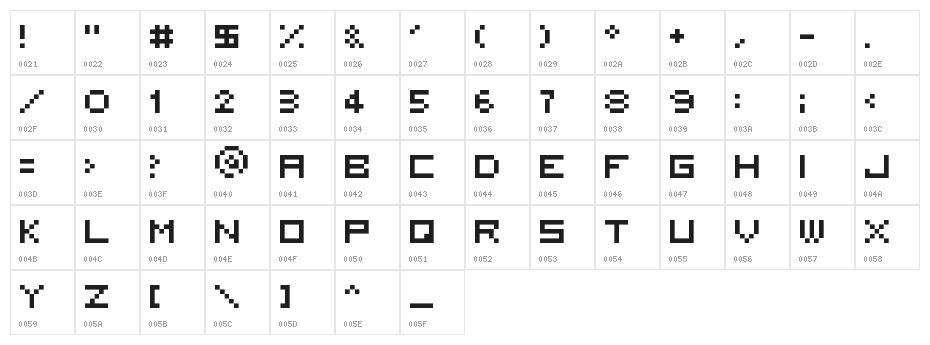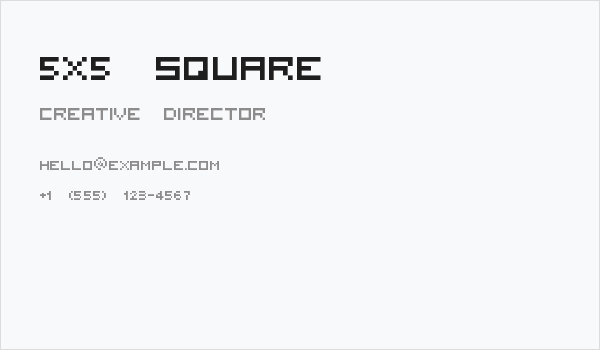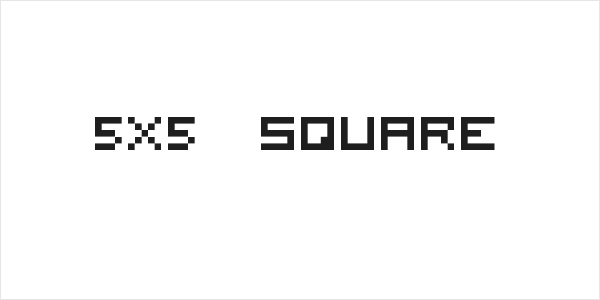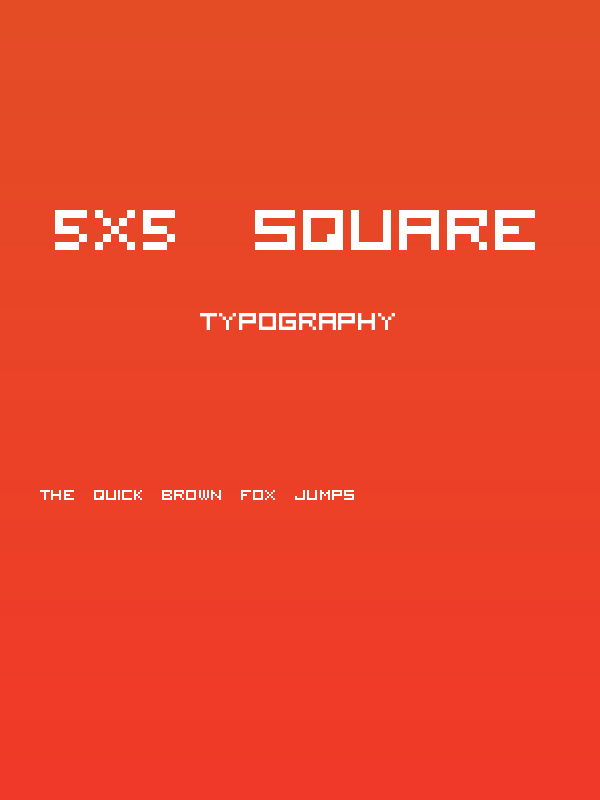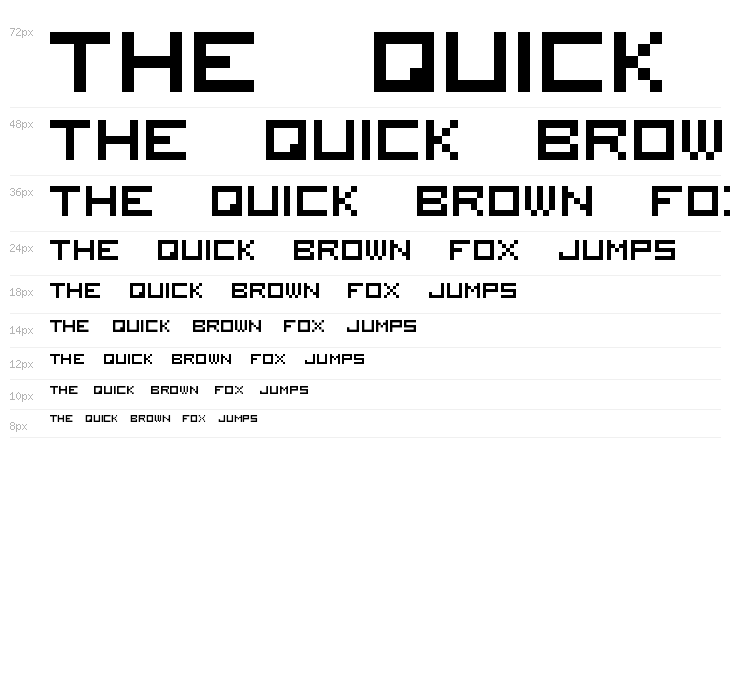
5x5 square Font
| Gesamtstil | Vintage |
| Anwendungsfall | Headlines, Logos, Digital interfaces |
| Vorgeschlagene Projekte | Ideal for retro-themed designs, video game interfaces, digital art projects, and any creative work that seeks to evoke a sense of nostalgia for early computing. |